싸인에 나만의 로고를 더하면 더욱 특별한 의미를 가질 수 있어 요. 로고는 단순한 디자인이 아니라, 개인의 브랜드를 나타내는 강력한 요소랍니다. ✨
많은 연예인, 스포츠 선수, 사업가들이 단순한 서명 대신 로고화된 싸인을 사용해요. 예를 들어, 마이클 조던의 "Jumpman" 로고나, 일론 머스크의 간단한 필기체 싸인처럼 말이죠.
내가 생각했을 때, 로고 싸인은 단순한 글씨를 넘어 개인의 아이덴 티티를 나타낼 수 있는 최고의 방법이에요. 오늘은 싸인에 나만의 로고를 추가하는 방법을 알려드릴게요! ✍
나만의 로고가 들 어간 싸인의 의미
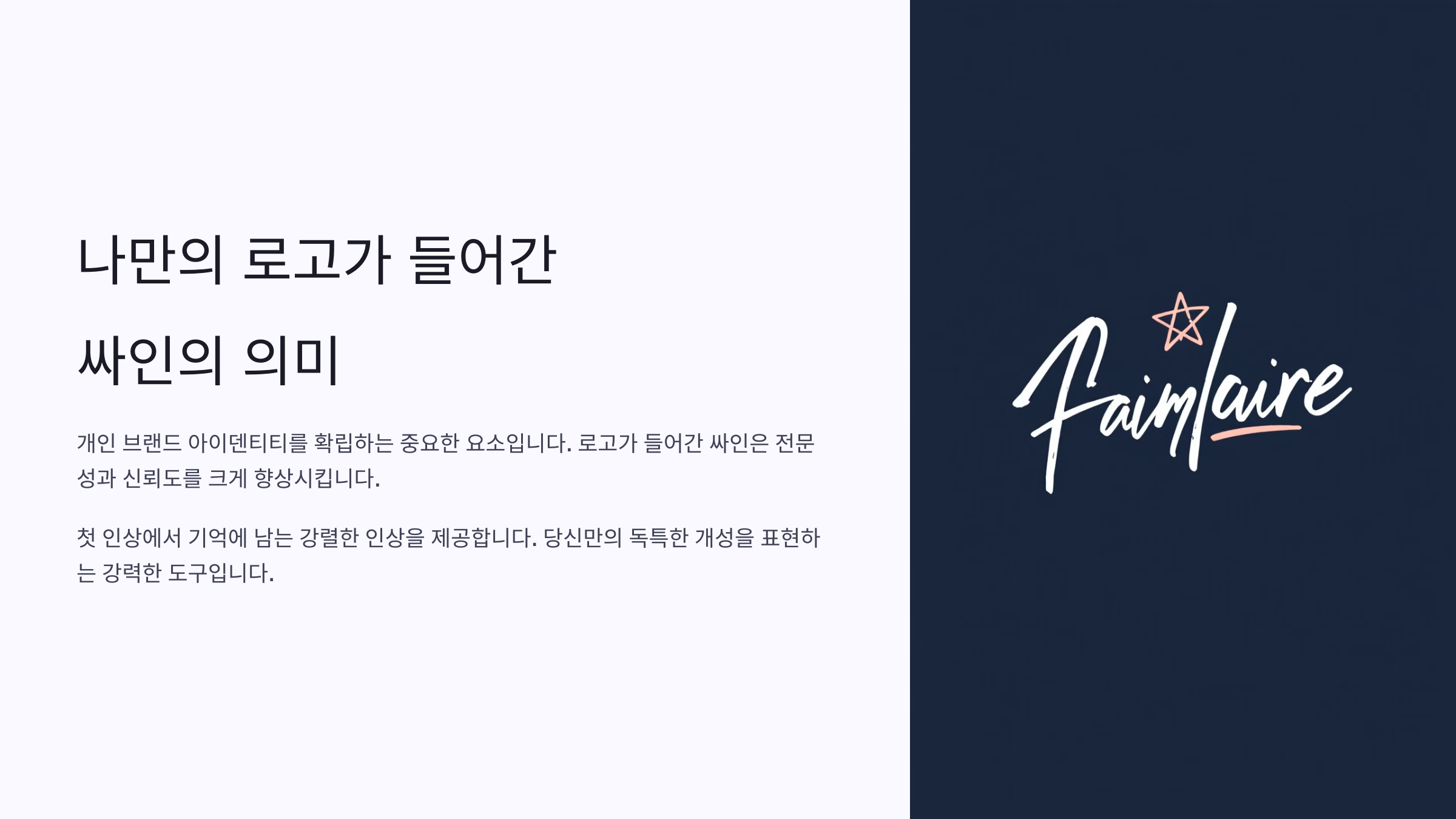
싸인에 로고를 추가하면 개성, 브랜드 가치, 시각적 임팩트를 높 일 수 있어요. 이것은 단순한 이름 서명과는 차별화된 강렬한 인상을 주죠.
특히 사업가, 예술가, 인플루언서라면 자신을 대표하는 아이콘이 필요해요. 로고가 포함된 싸인은 명함, 상품 패키지, 공식 문서 등에 활용하기에도 좋아요.
싸인에 로고를 더할 때 얻을 수 있는 장점
장점 설명 브랜드 강화 개인의 정체성을 시각적으로 표현 차별화 단순한 서명보다 눈에 띄는 효과 기억에 남는 디자인 사람들 이 쉽게 인식할 수 있음 이제 싸인에 어떤 요소를 추가하면 로고화될 수 있는지 알아볼까 요?
로고 싸인을 만들기 위한 기본 요소
싸인에 로고를 더할 때는 어떤 요소를 포함할지 고민해야 해요. 단순한 글씨 스타일뿐만 아니라, 로고를 구성하는 도형, 기호, 아이콘 등을 활용하면 더욱 특 별한 싸인이 완성될 수 있죠. ✍
예를 들어, 별(★), 동그라미(○), 삼각형(△) 같은 도형을 포함하거나, 이니셜을 활용한 독창적인 디자인을 만들 수 있어요. 숫자나 자신을 상징하는 작은 그림을 넣 는 것도 좋은 방법이에요.
로고 싸인을 구성하는 주요 요소
요소 설명 이니셜 활용 이름의 첫 글자를 강조하여 로고화 기호 추가 별(★), 하트(♥), 왕관() 등 자신만의 상징 도형 디자인 동그라 미, 삼각형 등 간단한 도형 추가 필기체 스타일 부드러 운 곡선으로 세련된 느낌 이제 싸인에 로고를 추가하는 단계별 제작법을 알아볼까요?
단계별 나만의 로 고 싸인 제작법 ✍
이름을 다양한 스타일로 써보기 먼저 기본적인 싸인을 여러 번 써보세요. 필기체, 대문자, 초성 스타일 등 다양한 변형을 시도해 보면서 어떤 스타일이 가장 마음에 드는지 찾는 것이 중요해요.
이니셜을 활용해 디자인하기 이름의 첫 글자를 강조하거나, 두세 글자만 조합해 간결한 로고 스타일로 변형해 보세요. 예를 들어 "김지훈"이라면 "KJH"를 활용할 수 있어요.
기호나 도형 추가 자신만의 개성을 살릴 수 있는 별(★), 동그라미(○), 번개⚡ 같은 기호를 추가해 보세요. 심플하면서도 강렬한 인상을 줄 수 있어요.
필압 조절로 세련된 느낌 연출 싸인의 선 굵기와 필압을 조절하면 더욱 멋진 로고 싸인이 완성될 수 있어요. 글자의 첫 부분을 강하게, 마지막을 부드럽게 처리하는 것도 좋은 방법이에요.
Q1. 싸인에 로고를 추가하면 법적으로 문제가 되나요?
A1. 아니요! 싸인은 본인을 식별할 수 있다면 자유롭게 디자인할 수 있어요.
Q2. 싸인 로고를 너무 복잡하게 만들면 안 될까요?
A2. 너무 복잡하면 기억하기 어렵고, 재현하기 힘들 수 있어요. 심플 하면서도 개성 있는 디자인이 가장 좋아요.
Q3. 싸인에 색상을 추가해도 되나요?
A3. 가능하지만, 일반적으로 공식 서명에서는 단색(검은색, 파란색) 을 사용하는 것이 일반적이에요.